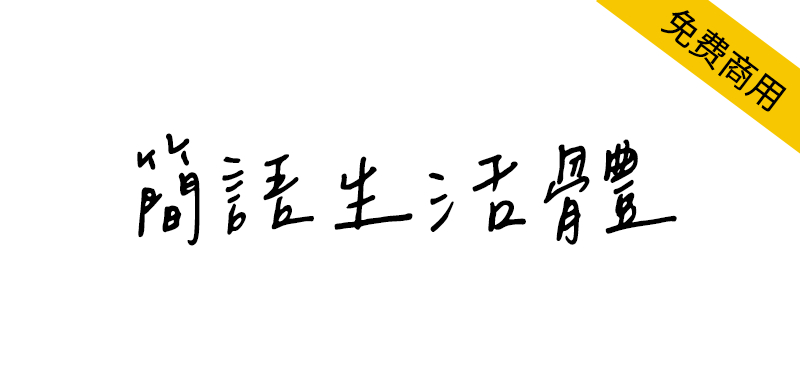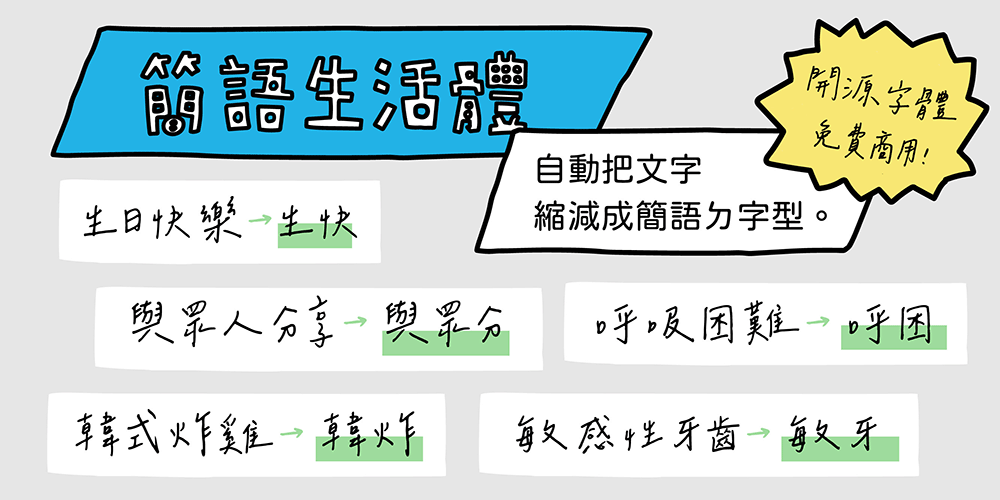
计划缘起:简语,一直都在我们的社会中。不是只有傳小、敏牙、情勒等年轻世代的流行语。央行、健保、地檢署,也都是我们习以为常的简语。不只有效率,也是生活情趣。人人之间的小暗号,让关系更加紧密。作为设计人,我们相信那句名言:「少即是多(Less is More)」——在2025的愚人节,justfont邀你一起庆祝简单的沟通。话少了,效率增加了,乐趣更多了。本着Less is More的精神与字体的专业,justfont提出完美的简语解决方案:字体档。
使用效果:文字承载着语言。在这个时代表现简语最佳的形式,理当是字体档。只要输入文字如台北車站、中央銀行、全民健康保險,甚或永遠支持、傳統小吃、飯店早餐,「简语生活体」就会自动浓缩为北車、央行、健保、永支、傳小、飯早等简语。
规格简介:简语生活体是基于辰宇落雁体字体修改而来,由justfont团队搜罗时下流行简语、常见台湾上市公司简称以及经典常用简语等超过1000个词条制作而成。透过OpenType的连字技术,制作出输入特定词语时,就会自动替换为相关简语的开源繁体中文字体。